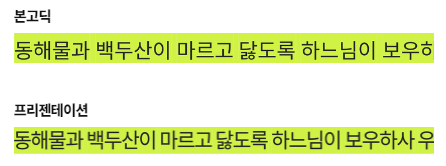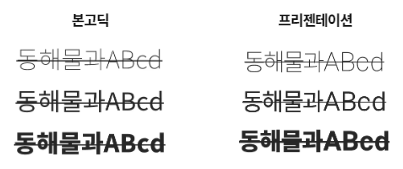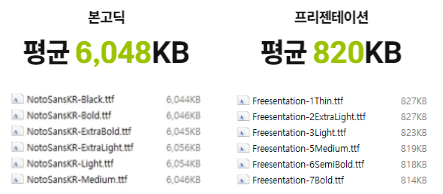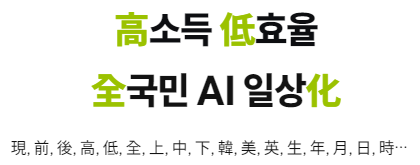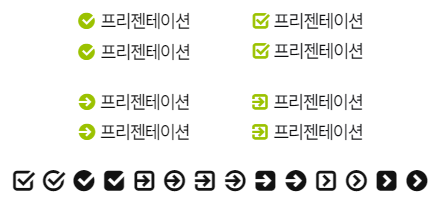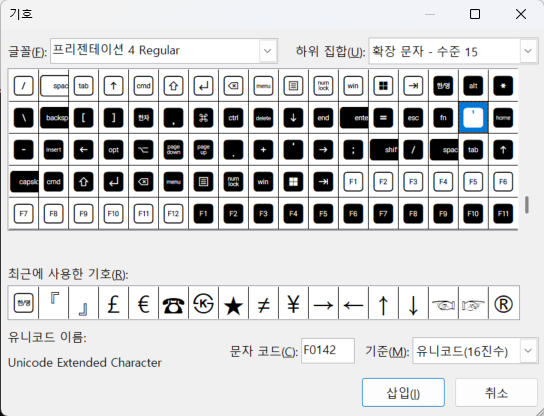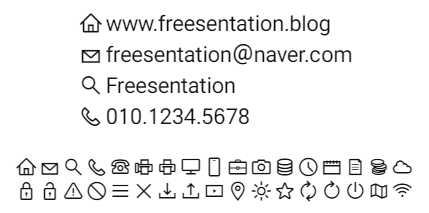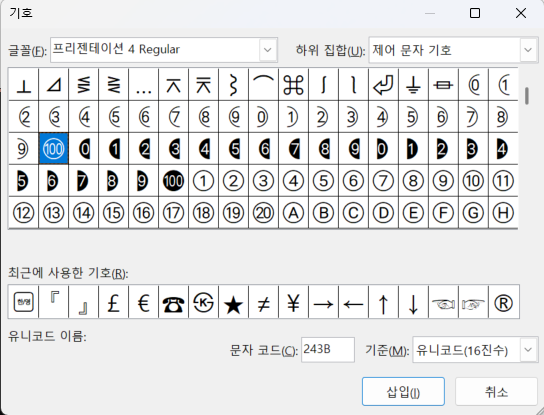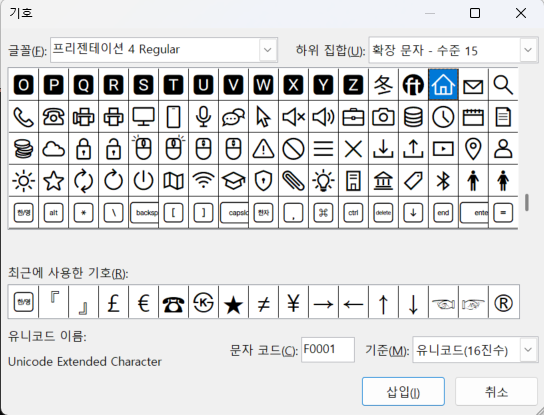
이번에는 다양한 용도로 활용이 가능한 무료 폰트, "프리젠테이션(Freesentation)" 폰트를 살펴볼까 합니다.
제안서, 보고서 등 파워포인트를 활용한 문서 작성을 많이 진행하고 있습니다. 파워포인트로 작업을 하다 보면 폰트의 장평이 너무 옆으로 넓거나 폰트의 굵기 등이 한정적인 폰트가 많아 내용을 강조하는데 어려움이 겪곤 합니다.
이 폰트를 제작하고 공유해 주신 이주임 디자이너도 18년차 프레젠테이션 디자이너라고 하십니다. 이 폰트를 제작하게 된 계기를 짧게 작성해 두셨기에 공유해 봅니다.
오랫동안 파워포인트로 PT 디자인을 해오면서 폰트 사용에 있어서 불편한 점들을 개선하면 좋겠다는 막연한 생각을 해왔습니다.
그러다 이렇게 폰트를 만들게 되었네요. 오픈소스를 활용하여 만들었지만 폰트제작은 처음인지라,
다소 미숙한 점이 있더라도 노여워 마시고, 친절하게 말씀주시면 차근차근 보완해 나가겠습니다.
폰트 디자인이라는게 잘은 모르지만 일반 디자이너들이 그냥 하고 싶다고 할 수 있는 분야는 아닌 거 같은데 대단한 거 같습니다.
앞서 언급한 것과 같이 파워포인트로 프레젠테이션 문서를 작성하다 보면 폰트가 맘에 들지 않는 경우가 왕왕 있는데 같은 고민을 하다가 자주 사용되는 폰트를 가공하여 프레젠테이션에 특화된 형태의 폰트를 제작하신 것으로 생각됩니다.
프리젠테이션(Freesentation) 폰트는 한글 베이스 폰트와 영문 베이스 폰트가 다르게 구성되어 있습니다.
한글 폰트는 본고딕(Noto Sans), 영문 폰트는 Roboto 폰트를 결합하여 파워포인트 사용성을 중심으로 제작된 폰트입니다.
참고로 본고딕(Noto Sans) 폰트는 어도비와 구글이 동아시아의 여러 글꼴 회사와 같이 같이 제작하여 2014년에 오픈 소스로 공개한 CJK 산세리프 글꼴로 SIL 오픈 폰트 라이선스로 배포되었습니다. 한국어 디자인은 산돌커뮤니케이션에서 진행하였습니다.
그래서 어도브에서는 본고딕 Source Han San라는 이름으로 구글에서는 Noto Sans CJK라는 이름으로 2개의 명칭으로 혼용되고 있습니다.
* CJK - 중국어(중국 본토 간체, 대만 정체, 홍콩 번체), 일본어, 한국어(옛 한글 포함) 지원
단순히 2가지 폰트를 엮어서 재구성한 것이 아닌 파워포인트 작업을 하면서 느꼈던 불편한 부분들을 개선해 보고자 만들어진 폰트로 몇 가지 특징이 있습니다.
1. 읽기 전용이 아닌 수정 가능한 폰트
파워포인트 옵션에서 "글꼴 포함"을 체크하면 폰트가 없는 컴퓨터에서도 수정이 가능합니다.
2. 폭이 좁은 장체 스타일로 글자를 더 크게 더 많이
글자 너비와 글자 사이 간격을 좁게하여 같은 공간에 더 큰(또는 더 많은) 글자를 담아낼 수 있습니다.
3. 문자 간격은 쫀쫀하게 줄 간격은 시원하게
번거로운 간격 조정은 이제 그만. 기본 간격 그대로 사용해도 보기 좋은 형태로 출력됩니다.
4. 텍스트 운곽선을 넣지 않아도 작은 글씨까지 깔끔하게
더 이상 텍스트에 투명한 윤곽선을 넣지 않아도 깔끔한 글씨가 출력됩니다.
5. 한 눈에 알아보기 쉽게! 딱 떨어지는 고정폭 숫자
숫자 1의 폭을 동일하게 하여 꼼마와 소수점 자리 맞춤 가능, 이 부분은 호불호가 갈릴 수 있는 부분이라 가변형 글자까지 제작해 둔 것으로 보입니다.
6. 챕터 타이틀을 위한 Slab Serif 로마 숫자
밋밋한 고딕체 로마 숫자에 명조 한 스푼 추가, 누가 봐도 로마 숫자스럽게!!
7. 파워포인트에서도 들뜸없이 촘촘한 커닝
파워포인트에서 적용되지 않던 커닝 문제를 해결했습니다.
8. 텍스트 상자 위, 아래 간격을 동일하게
텍스트가 도형 중심에 잘 위치하도록 수직 메트릭스를 맞추었습니다.
9. 글자 높이에 맞춘 형광펜 두게 맞춤
형광펜이 너무 위로 올라오지 않도록 글자에 맞게 수정!
10. 디테일 무엇?! 취소선 중심 맞춤
취소선 중심은 물론, 텍스트 굵기에 따라 취소선의 굵기도 조절했어요.
11. 한글과 영문(숫자) 사이즈 균형 맞춤
크고 짧은 글이 많은 PT의 특성상 큰 글자에서도 영문이 작아 보이지 않도록 영문 비율을 더 키웠어요.
12. 한글 2,780자 기본 음절로 가벼운 용량
파워포인트에 글꼴 포함 하기에도 부담없는 파일 크기(ver 1.003 기준 820kb)
한자가 추가된 ver. 1.004 버전은 1.4mb, 전체 한글(11,172자) 추가된 ver. 2.000 버전은 3mb 로 기존 본고딕 대비 최대 76% 용량 감소
13. 중고등 필수 한자 1,800자(선택 포함)
본고딕(Noto Sans)의 중국어 8천 여개의 글자 중 필수 한자 1,800자 포함(ver. 1.004 버전 부터)
14. 다양한 모양의 글머리 기호
체크표시와 화살표를 도형과 결합하여 새로운 글머리 기호 추가
글머리 기호는 사용자 지정에서 '사용자 정의 영역'을 눌러서 찾을 수 있습니다.
15. 동글동글 예쁜 따옴표와 한글 높이에 맞춘 괄호
그냥... 따옴표가 예뻤으면 했어요.
16. 맥과 윈도우 상관없이 동일한 표현
맥과 윈도우에서 글꼴이 다르게 나와서 많이 불편하셨죠?
17. 백번까지 거뜬 반원 숫자
원 숫자가 20번까지 밖에 없어서 아쉬우셨죠?
반원 숫자는 기호에서 '제어문자기호'에 있습니다.
18. 강사님들을 위한 Keycap
키캡 따로 찾지 마세요~ 여기 다 있어요!!
키캡은 기호창 제일 아래 '확장문자'에 있습니다.
19. 자주 쓰는 기본 아이콘
아이콘 찾으러 다니지 마시고, 텍스트와 함께 사용하세요!
아이콘은 기호창 제일 아래 '확장문자'에 있습니다.
20. 윈도우에서는 폰트 없이도 다른 파일에 복붙 가능
글꼴 포함된 문서를 폰트가 없는 컴퓨터에서 내용을 복사해 다른 파일 또는 새 파일에 붙여 넣으면 대부분은 폰트가 깨지지만 프리젠테이션은 깨지지 않아요! (단, 윈도우에서만 가능)
정말 프리젠테이션(Freesentation) 폰트의 특징은 우리가 그동안 문서 작성하면서 느꼈던 많은 불편 사항을 고민해서 개선해 준 폰트라는 생각이 듭니다.